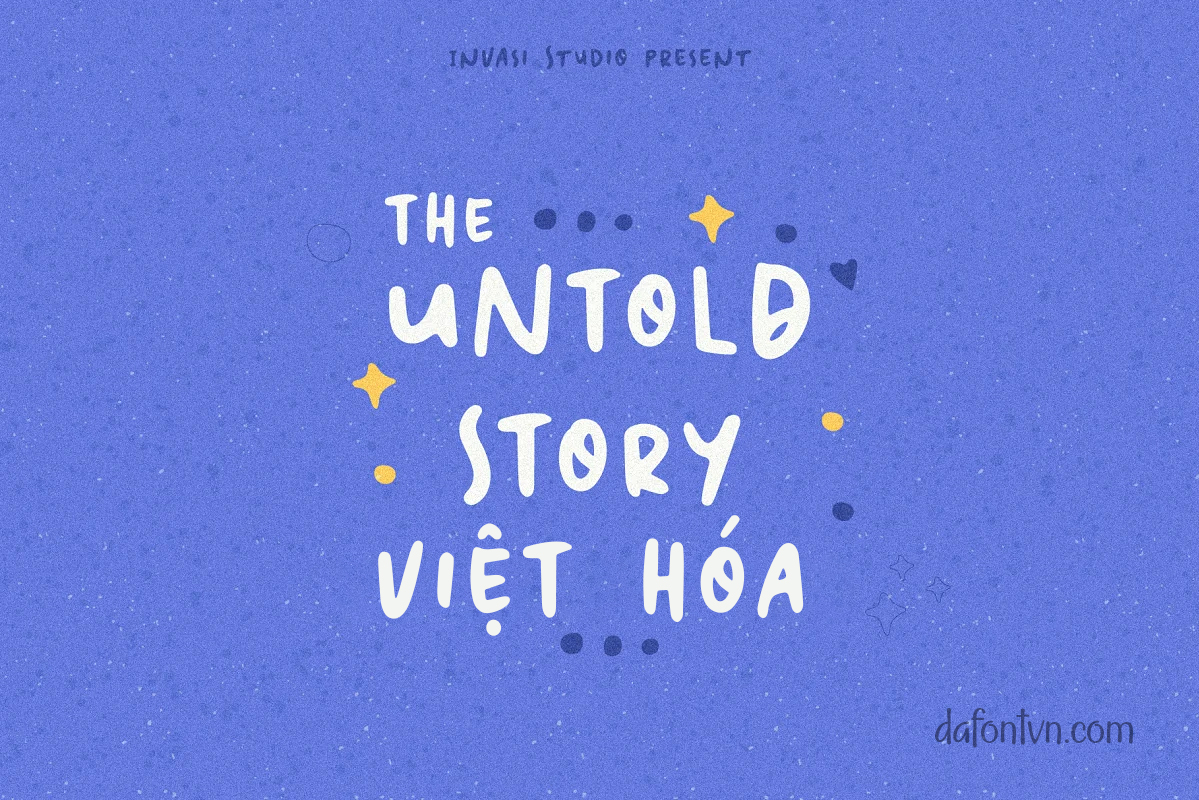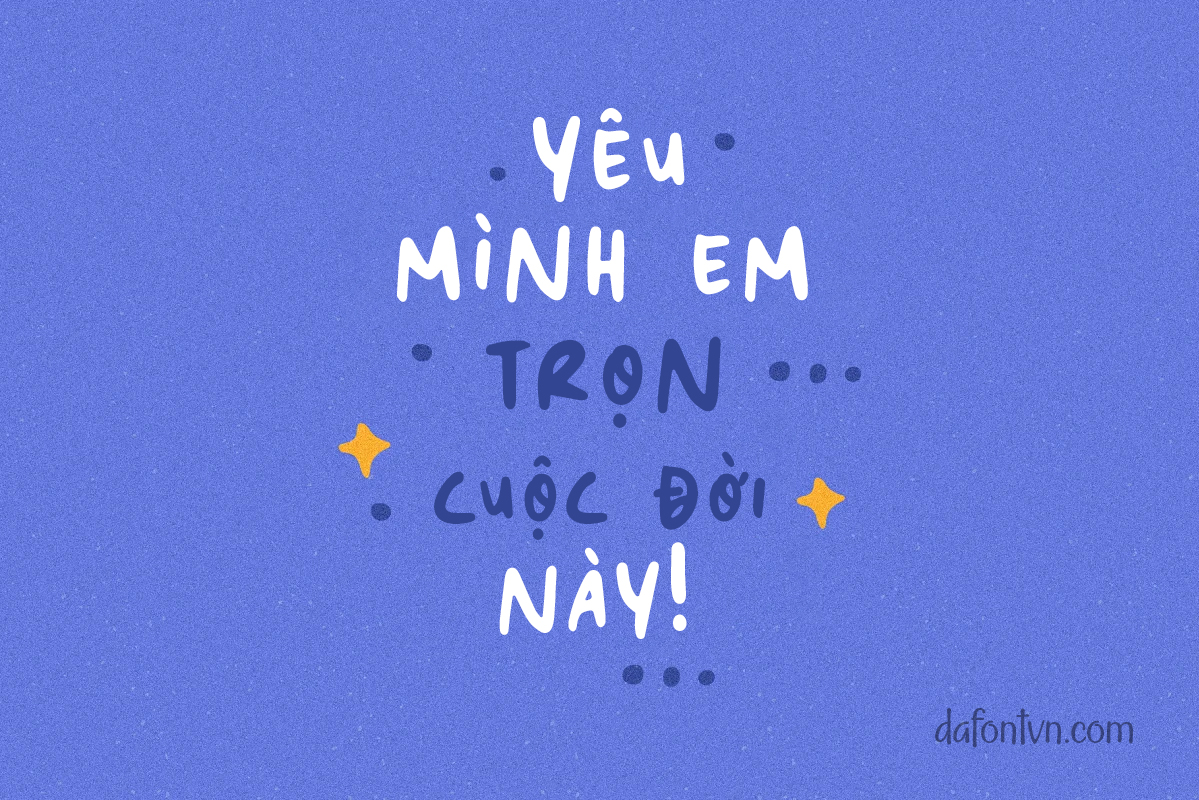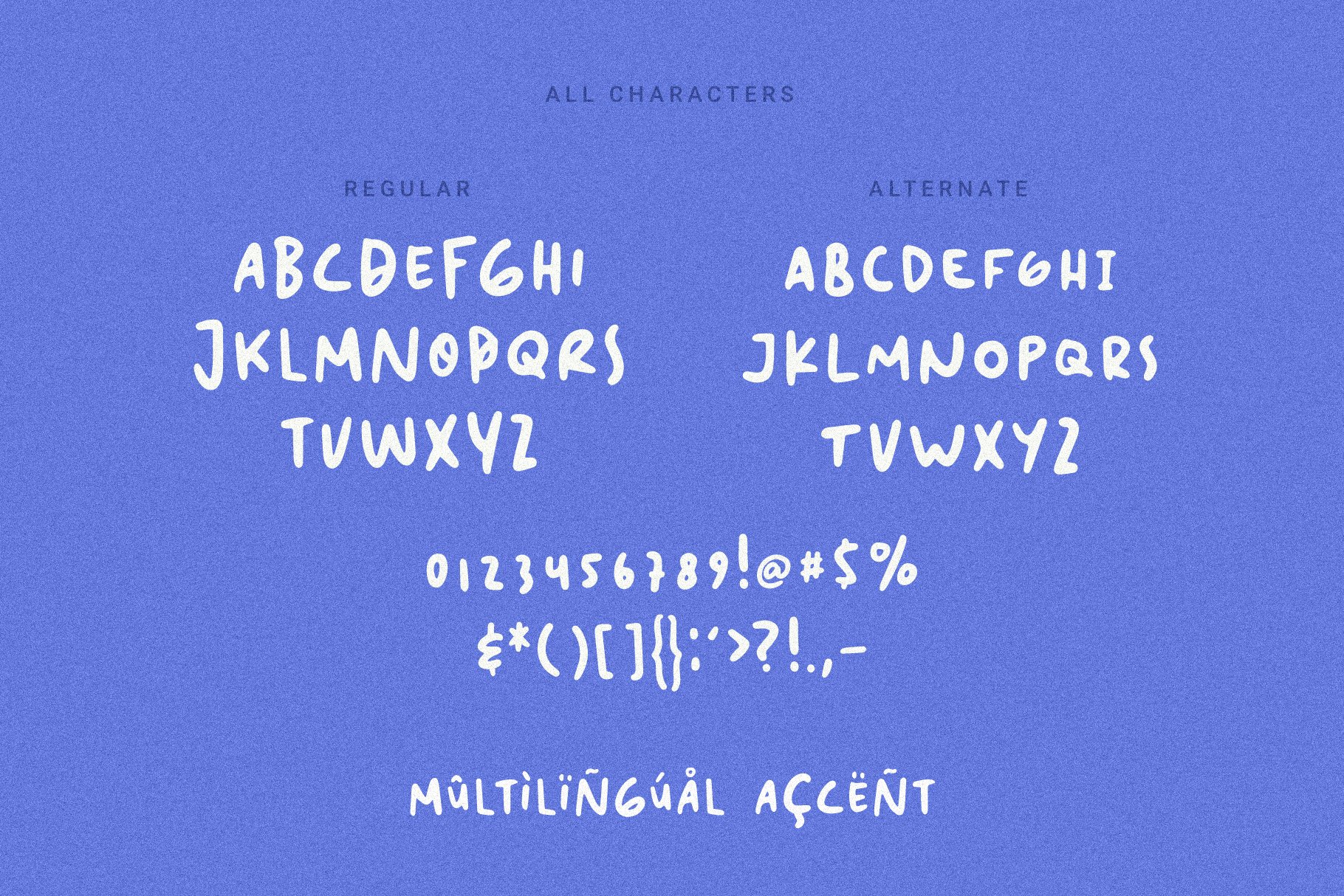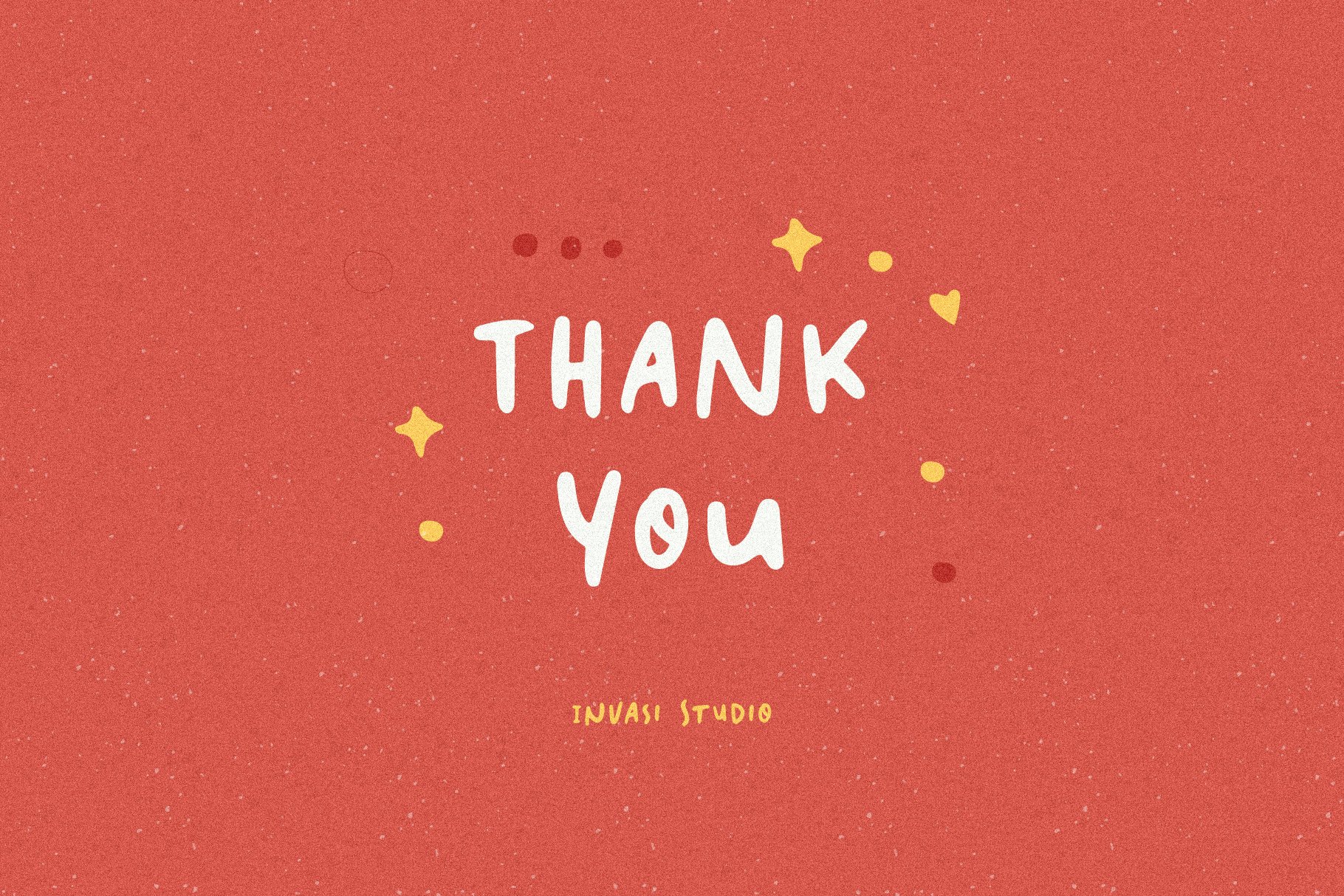
Untold Story Việt Hóa là một font chữ theo phong cách Brush và kéo dài kerning, đặc biệt đối với quote hiển thị, bạn có có thể sử dụng font này vào các dự án của bạn và sẽ truyền cảm hứng cho bạn để tạo ra một cái gì đó độc đáo hoặc tinh nghịch thiết kế.
Đặc trưng:
– Đa ngôn ngữ
– Thay thế
– Chấm câu
Font Untold Story Việt Hóa
Untold Story | Quotable Font Việt Hóa